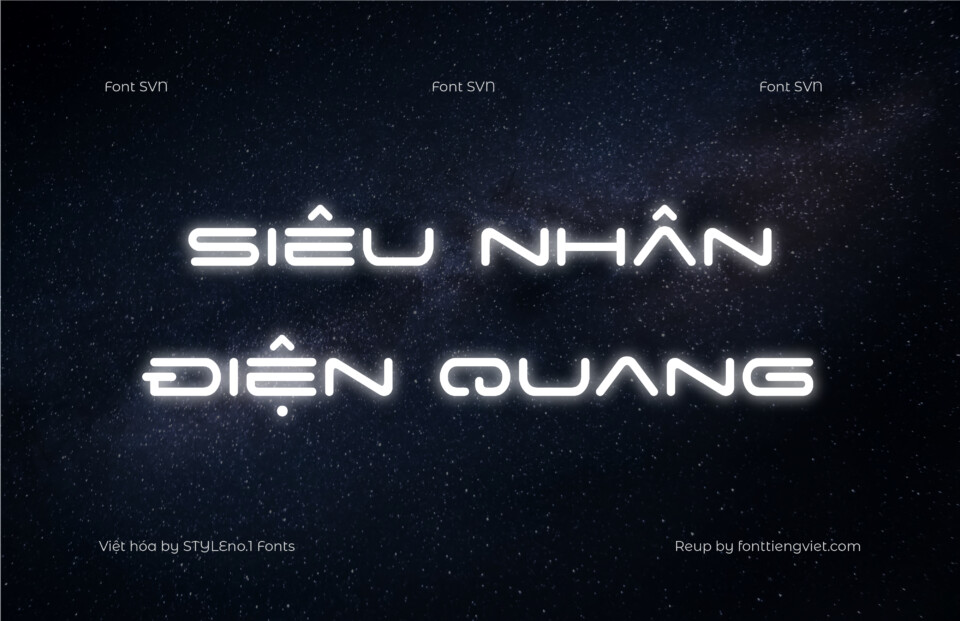
Font Việt hóa SVN Space Age
Giới thiệu về Font Việt hóa SVN Space Age
Trong thế giới thiết kế đồ họa hiện đại, việc tìm kiếm một bộ Font Miễn Phí có phong cách độc đáo luôn là ưu tiên hàng đầu của các bạn học sinh và sinh viên. Font Việt hóa SVN Space Age chính là lựa chọn hoàn hảo cho những ai yêu thích sự phá cách và muốn mang hơi thở của tương lai vào trong các bài thuyết trình hay dự án sáng tạo cá nhân. Đây là kiểu chữ được lấy cảm hứng mạnh mẽ từ các bộ phim khoa học viễn tưởng, mang đến vẻ ngoài tối giản nhưng cực kỳ mạnh mẽ với những đường nét bo tròn tinh tế và các góc cắt sắc sảo đặc trưng.
Đặc điểm nổi bật của Font Việt hóa SVN Space Age
Thiết kế mang tính đột phá và hiện đại
Kiểu chữ này không chỉ đơn thuần là các ký tự mà còn là một tác phẩm nghệ thuật hình khối. Font Việt hóa SVN Space Age giúp người dùng dễ dàng tạo ra những tiêu đề ấn tượng, thu hút ánh nhìn ngay từ giây phút đầu tiên. Các chữ cái được thiết kế đồng nhất về độ dày, tạo cảm giác ổn định và chuyên nghiệp cho mọi khung hình.
Khả năng ứng dụng linh hoạt trong học tập
Dù bạn đang thực hiện một poster cho câu lạc bộ trường học hay trang trí bìa tiểu luận, bộ font này đều đáp ứng tốt nhờ tính thẩm mỹ cao. Với bộ mã Unicode đã được việt hóa hoàn chỉnh bởi SVN, các bạn có thể yên tâm sử dụng tiếng Việt có dấu mà không lo bị lỗi hiển thị hay mất nét chữ.
Lưu ý khi sử dụng và kết luận
Để đạt được hiệu quả thị giác tốt nhất, bạn nên kết hợp Font Việt hóa SVN Space Age với các tông màu neon hoặc nền tối để làm nổi bật tinh thần công nghệ. Đây thực sự là công cụ hỗ trợ đắc lực cho cộng đồng thiết kế trẻ tại Việt Nam. Hãy nhanh tay truy cập Font Miễn Phí, Font Việt Hóa, Font Việt hóa SVN Space Age để tải về và bắt đầu hành trình sáng tạo những sản phẩm đậm chất không gian của riêng mình ngay hôm nay.